폰트 페어링 기본 원칙과 실패 피하는 법
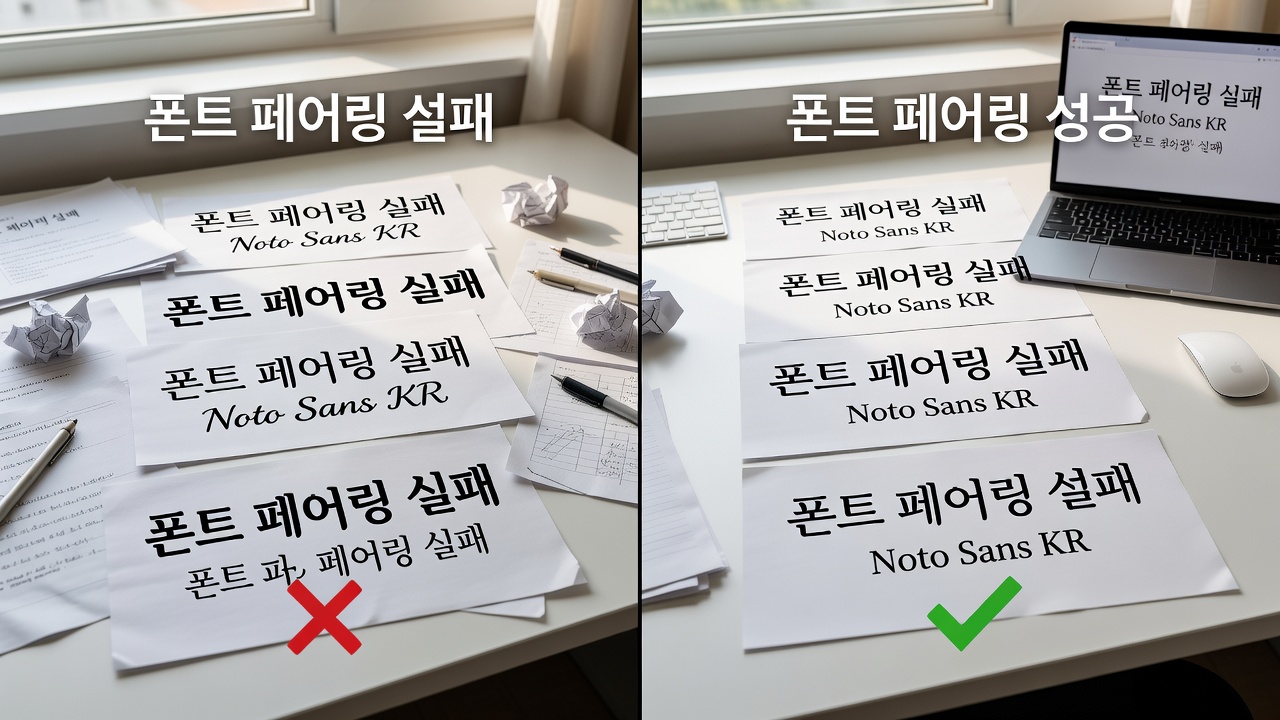
폰트 페어링 기본 원칙과 실패 피하는 법
폰트 페어링은 대비와 조화를 동시에 고려해야 성공합니다. 서로 다른 폰트가 시각적으로 충돌하지 않으면서도 정보 계층을 명확히 전달할 수 있어야 하며, 이는 타이포그래피의 기본적인 성공 조건입니다. 2026년 현재에도 이 원칙은 디지털·인쇄 디자인 전반에서 변함없이 적용되고 있습니다.
폰트 페어링의 기본 개념
폰트 페어링은 두 개 이상의 서체를 조합해 하나의 디자인 시스템을 만드는 작업입니다. 단순히 예쁜 폰트를 나란히 놓는 것이 아니라, 글자 크기·굵기·스타일의 차이를 통해 정보의 우선순위를 표현하는 것이 핵심입니다.
2026년 현재 대부분의 디지털 인터페이스에서는 본문용과 제목용 서체를 명확히 구분하는 것이 표준이 되었습니다. 이 구분이 제대로 이루어지지 않으면 독자는 텍스트를 읽는 데 불필요한 인지 부하를 느끼게 됩니다.
대비와 조화의 균형 원칙
성공적인 페어링의 첫 번째 조건은 대비입니다. serif와 sans-serif를 섞거나, 굵기 차이를 확실히 두는 방식이 대표적입니다. 다만 대비가 과도하면 전체적인 통일감이 깨질 수 있으므로, 한두 가지 요소에서만 강한 차이를 주는 것이 안전합니다.
두 번째 조건은 조화입니다. 글자 너비, x-height, 곡선의 부드러움 정도가 비슷한 폰트끼리 함께 사용하면 시각적 안정감이 생깁니다. 이 두 조건을 동시에 만족시키는 것이 폰트 페어링의 기본 기술입니다.
흔한 실패 사례와 해결 방법
| 실패 유형 | 원인 | 해결 방향 |
|---|---|---|
| 스타일 과다 혼용 | 3종 이상의 폰트 패밀리 동시 사용 | 본문·제목·강조용으로 2종으로 제한 |
| x-height 불일치 | 세로 비율이 다른 폰트 조합 | 비슷한 x-height를 가진 폰트 선택 |
| 과도한 장식체 사용 | 제목과 본문 모두 장식체 적용 | 본문은 중립적인 sans-serif로 변경 |
이러한 실패는 대부분 “예쁘다”는 느낌만으로 폰트를 선택할 때 발생합니다. 실제로는 가독성과 계층 구조를 먼저 확인해야 합니다.
한글 타이포그래피에서의 페어링 전략
한글은 영문과 달리 자음·모음의 결합 구조가 복잡하기 때문에, 영문 대비가 강한 폰트와 함께 사용할 때는 특히 주의가 필요합니다. 최근에는 한글과 영문을 동시에 지원하는 폰트 패밀리가 늘어나면서 페어링 부담이 줄어들고 있습니다.
한글 본문에는 Noto Sans KR이나 Pretendard 같은 중립적인 고딕체를 두고, 제목에는 약간의 개성이 있는 폰트를 얹는 방식이 안정적입니다. 영문과 한글을 함께 배치할 때는 영문의 x-height를 한글의 중간 획 높이에 맞추는 것이 시각적으로 자연스럽습니다.
실무에서 활용할 수 있는 도구
2026년 현재 폰트 페어링을 지원하는 도구로는 Google Fonts의 페어링 미리보기, Fontpair, Typewolf 등이 여전히 널리 사용됩니다. 특히 Google Fonts는 한글 폰트도 함께 제공하므로 한국어 프로젝트에서 실무적으로 활용도가 높습니다.
이 외에도 Figma의 플러그인이나 Adobe Fonts의 추천 기능을 활용하면 빠르게 여러 조합을 테스트해 볼 수 있습니다. 중요한 것은 도구에 의존하기 전에 직접 인쇄하거나 화면에 띄워 가독성을 확인하는 습관입니다.
단계별 페어링 실행 과정
- 콘텐츠 구조를 먼저 분석해 제목·부제·본문·강조 요소를 구분합니다.
- 본문용 폰트를 먼저 정한 뒤, 제목용 폰트를 선택합니다.
- 실제 레이아웃에 적용해 대비와 조화를 점검합니다.
- 인쇄 시안과 모바일 화면을 모두 확인한 후 최종 결정합니다.
이 과정을 반복하면 실패 확률을 크게 낮출 수 있습니다.
폰트 페어링을 할 때 폰트는 최대 몇 종까지 사용해도 되나요?
대부분의 경우 2종으로 충분합니다. 본문용 1종, 제목·강조용 1종으로 제한하는 것이 가독성과 통일성을 유지하는 데 유리합니다.
한글과 영문을 함께 쓸 때 어떤 점을 가장 주의해야 하나요?
x-height와 전체적인 너비 비율을 맞추는 것이 중요합니다. 영문이 한글보다 너무 작거나 커 보이지 않도록 미리 테스트해야 합니다.
무료 폰트만으로도 좋은 페어링이 가능한가요?
가능합니다. Noto Sans, Inter, Pretendard 같은 무료 폰트 조합만으로도 충분히 안정적인 결과를 얻을 수 있습니다.
페어링이 실패했다는 판단 기준은 무엇인가요?
본문을 읽을 때 눈이 피로하거나, 제목과 본문의 관계가 명확하지 않다면 실패한 것입니다. 인쇄하거나 실제 기기에서 확인하는 것이 가장 정확합니다.
기존에 사용하던 폰트 조합을 바꾸고 싶을 때는 어떻게 시작해야 하나요?
먼저 현재 조합의 문제점을 구체적으로 정리한 뒤, 한 가지 요소만 바꿔 테스트하는 것이 좋습니다. 한 번에 여러 폰트를 교체하면 원인을 파악하기 어렵습니다.